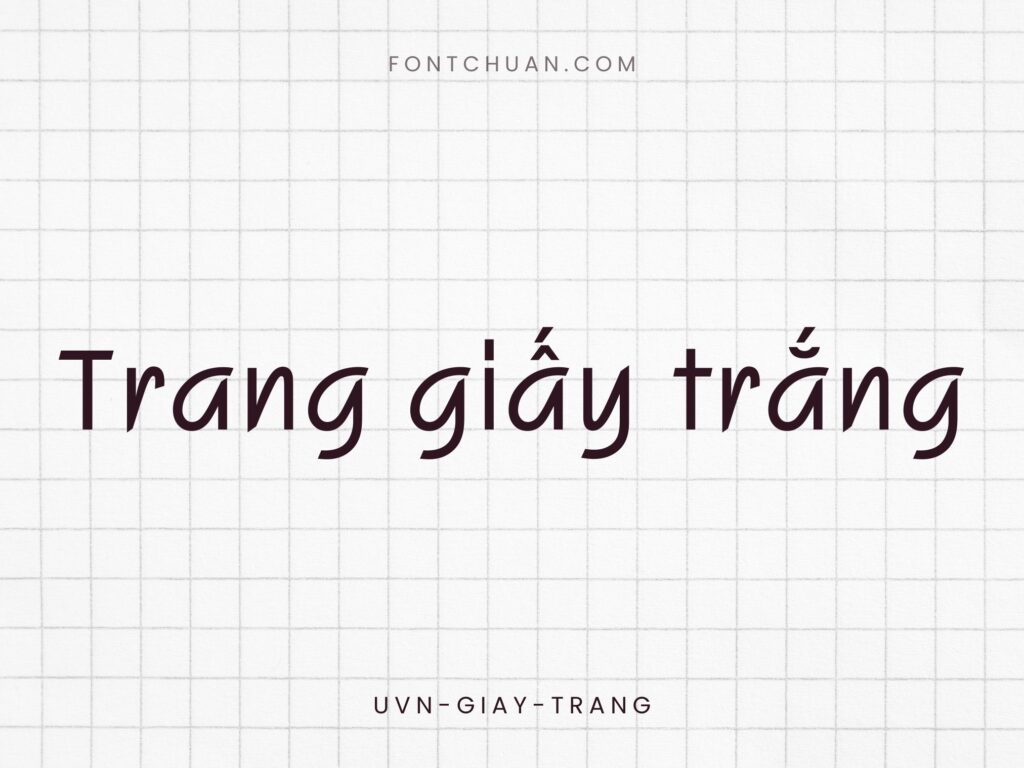
Font UVN Giay Trang Việt Hóa
UVN Giấy Trắng là một kiểu chữ thư pháp mang phong cách viết tay truyền thống, với các đường nét mềm mại và uyển chuyển, tạo cảm giác nghệ thuật và cổ điển. Font này chỉ được sưu tầm và đăng bởi thành viên của Font Chuẩn.
UVN Giấy Trắng có cấu trúc chữ với các nét thanh mảnh và độ nghiêng nhẹ, tạo nên sự duyên dáng và dễ đọc. Font này phù hợp cho các ứng dụng như thiết kế thiệp mời, tiêu đề, biển hiệu và các ấn phẩm in ấn yêu cầu sự trang nhã và nghệ thuật. Các ngành nghề như quảng cáo, giáo dục, công nghệ và bất động sản có thể tận dụng UVN Giấy Trắng để tạo điểm nhấn độc đáo trong thiết kế.